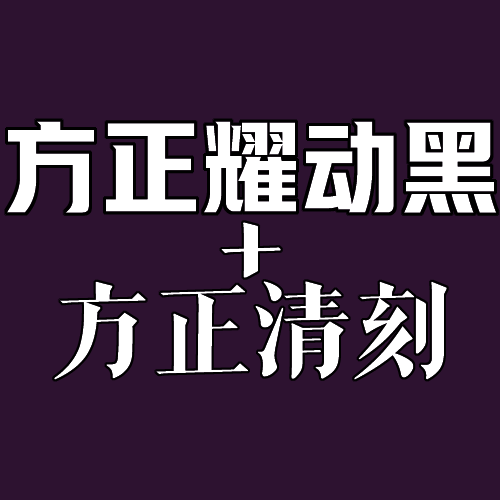
Better Chinese Fonts Ultimate
此模组是“更好的中文字体”的补充版,包含了30000+字符,原模组见https://steamcommunity.com/sharedfiles/filedetails/?id=3029640969
如果你对苍白无力的原版字体或是中规中矩的52字体感到腻味,那么恭喜你找到了这款模组!
本模组为字体修改模组,为中英文提供了两种字体:方正清刻本悦宋,主要用于地图和部分数字、拉丁字符;方正耀动黑,用于其他文字。